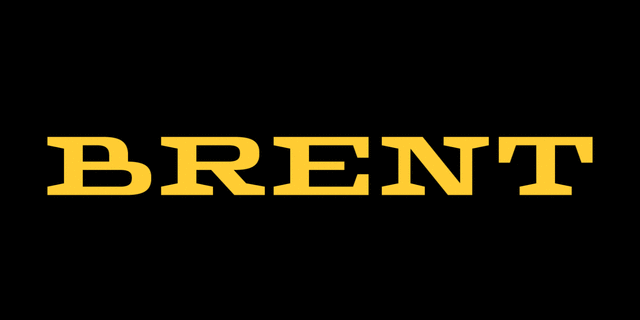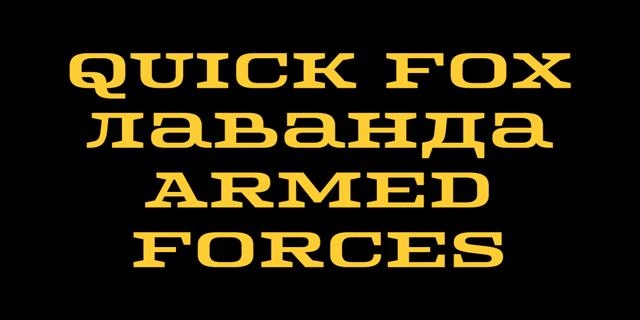
Brent 4F - широкий брусковый шрифт для вывесок, упаковки и логотипов в духе 50-х. Подойдет для всего, в чем важна надежность, высокое качество и традиции. Шрифт разработан Сергеем Ткаченко в 2013 году.
Ассоциации c семейством Brent 4FКачества и характер:
громкий, просторный, ремесленный, мачо, ностальгический, консервативный, дорогой, сильный, оригинальный, выразительный, характерный, пафосный, амбициозный, авторитетный, властный, уверенный, богатый, традиционный, убедительный, внушительный, серьезный, значительный, обязательный, солидный, стабильный, качественный, добротный, четкий, ценный, самостоятельный, ответственный, западный, статичный, тяжелый, квадратный, броский, заметный, мотивирующий, блатной, устойчивый, винтажный, ровный, твердый, резкий, претенциозный, олдскульный, железный, прочный, надежный, крафтовый, бандитский, сексуальный
кузница, ремесло, джинсы, конюшня, лошадь, револьвер, гамбургер, деньги, банк, монета, алкоголь, табак, виски, финансы, суд, власть, ломбард, сейф, правосудие, мясо, экономика, карты, игра, сигары, обед, ужин, магазин, торговля, детектив, мафия, одежда, обувь, ресторан, бар, грузовик, дальнобойщик, инструмент, техника, сырье, нефть, топливо, автомобиль, станок, казино, трофей, награда Стилистика:
Особенности семейства Brent 4FХит десятилетия:
Хит 1950-х |